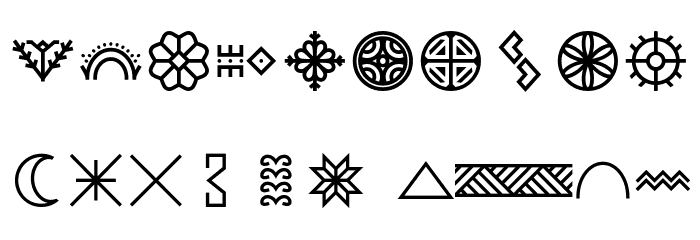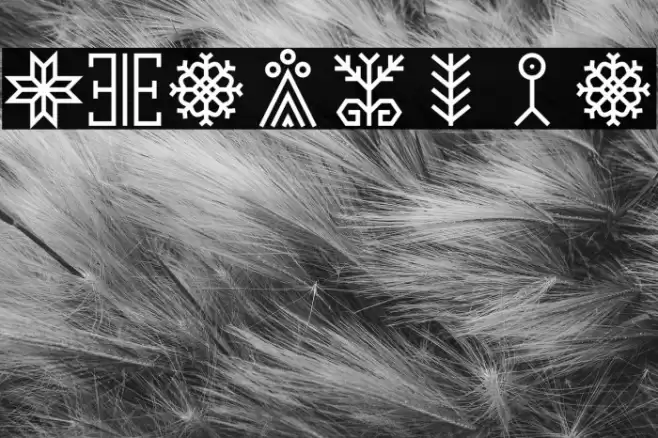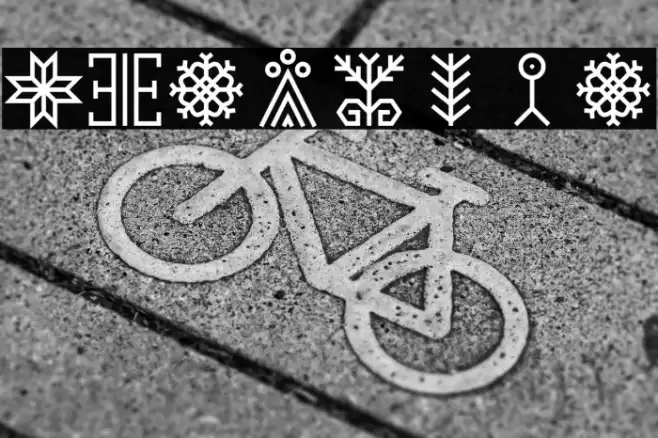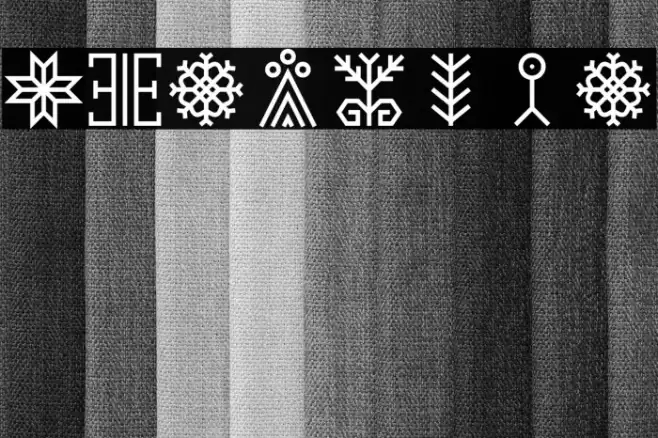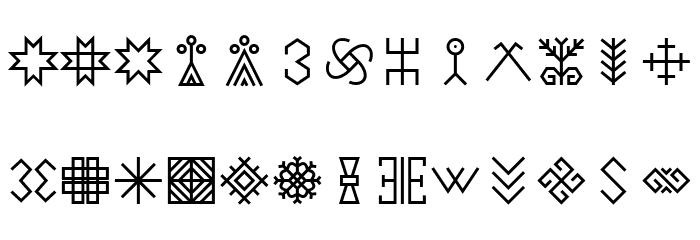
Auseklis Font
| Caso de uso | Logos, Decorative art, Cultural projects |
| Projetos propostos | Ideal for cultural artwork, decorative designs, and thematic branding. |